字体为王或您的内容有什么问题
已发表: 2019-12-23内容为王。 您肯定已经多次听到这个基本真理。 出于这个原因,您正在为数字项目的内容编写投入巨额预算。 但没有任何作用。 没有访客,没有排名,没有投资回报率……一句话,一切努力都是徒劳的。
为什么您的独特内容无效? 它不能到达你的观众吗? 你的营销工具总是无聊吗? 也许,原因比看起来容易。 从访问者的角度查看您的网页或横幅或登录页面。 你失败的原因可能是错误的字体。 这听起来很平庸。 但是让我们深入探讨字体在建立强大的在线形象方面的作用。
关于排版的统计数据是什么
排版是整个网站设计的一个组成部分。 它的元素会影响用户对内容的反应。 这是网站所有者与其受众之间的一种沟通方式。 但是,您几乎没有时间通过视觉工具吸引读者的注意力,因为:
- 91% 的在线用户倾向于使用具有视觉吸引力的内容,而不是基于文本的内容。
- 人类大脑处理视觉内容的速度比基于文本的速度快 60,000 倍。
- 大多数在线访问者阅读了页面上大约 20-28% 的整体文本。
- 55% 的网站访问者阅读帖子的时间不到 15 秒。
最后,每个网页设计师都知道“3 秒规则”。 网站吸引访问者注意力的时间非常有限。
由于人们花很短的时间阅读文本,网页设计师必须努力改进他们网站的排版。 使字体更赏心悦目和视觉吸引力是必须的。 它涉及基于文本和基于图像的字体。
因此,让我们找出有效的网络字体的主要需求。
使字体适用于您的项目的功能
网络上有近千种不同的 Google 字体系列可供免费使用。 嗯…… 一眼看去,选择最优秀的一两个很容易。 但是,这真的是一个艰难的选择。 此外,您应该在网页上根据其用途选择一种字体。 但是,任何字体都必须满足以下共同要求:
- 方便使用的;
- 清除;
- 易于阅读;
- 吸引人的;
- 值得信赖;
- 准确的。
除了广泛使用的默认 Helvetica 和 Arial 字体外,还有许多其他迷人但可读的字体。 让我们来看看其中的一些。
古董 - 豪华衬线字体字体
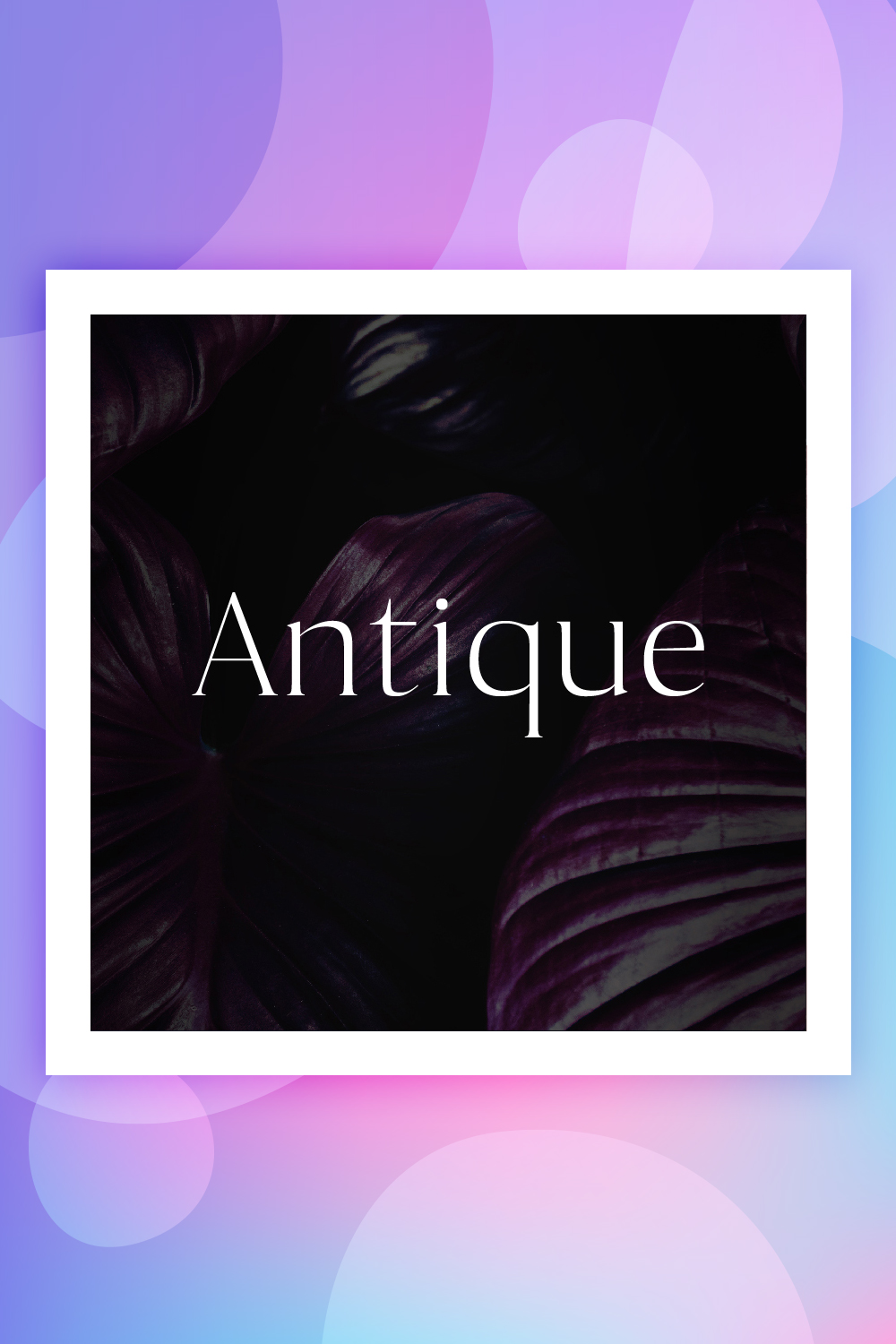
优雅清晰的排版爱好者会喜欢这种衬线字体。 古董看起来很经典,但并不普通。 这种字体略微弯曲,令人赏心悦目。 它看起来很适合多种需求。 您可以将其用于标题、横幅、基于文本的图像等。
Monalisa – Beauty Script 手写字体
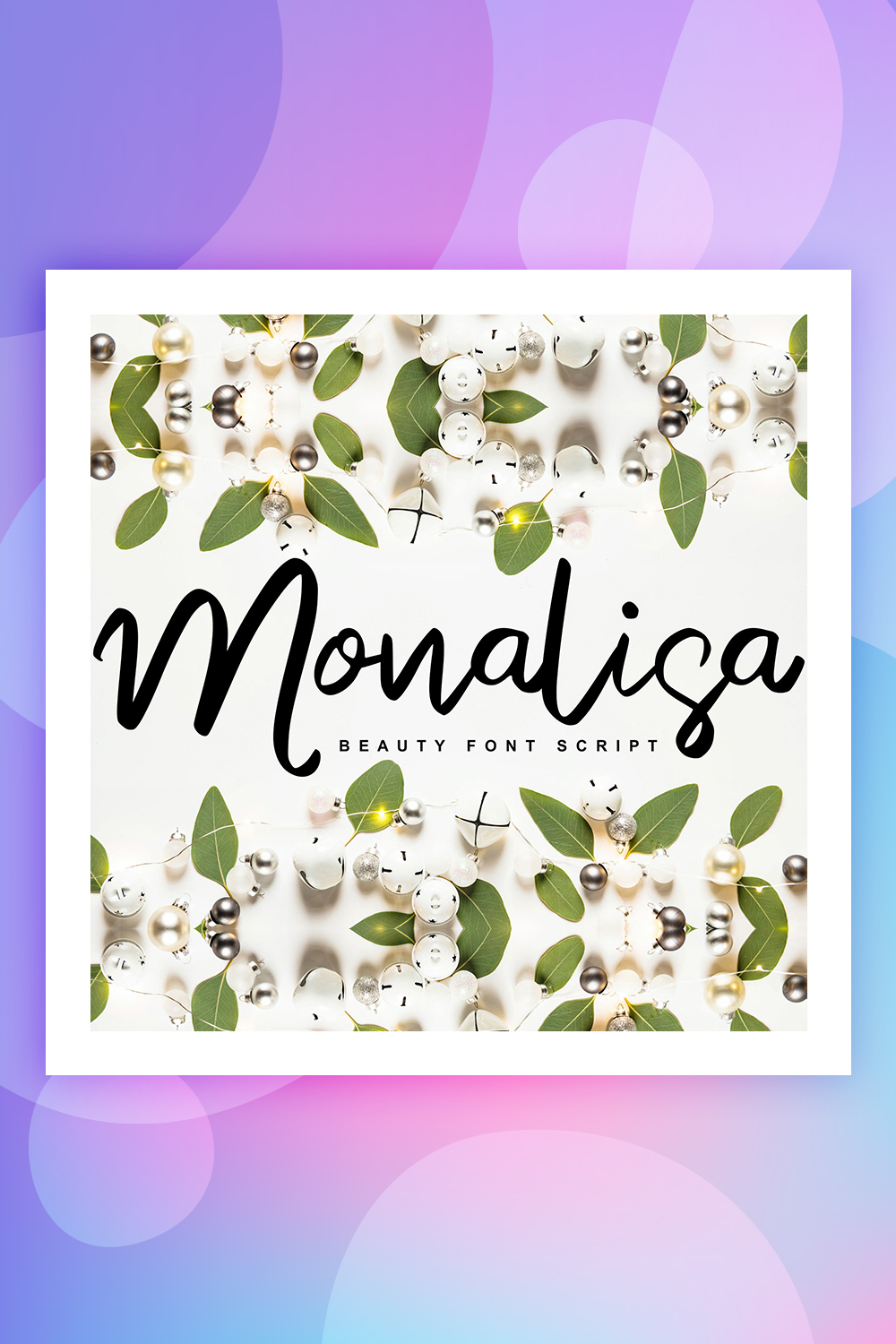
这种手写字体肯定会激发许多网页设计师的灵感。 蒙娜丽莎具有书法风格。 它可以为贺卡、邀请函、名片和品牌帖子提供真正的装饰。 通过使用这种字体,您可以使您的数字项目(例如,女性博客)在网络上大放异彩。
Qutapy – 现代脚本排版
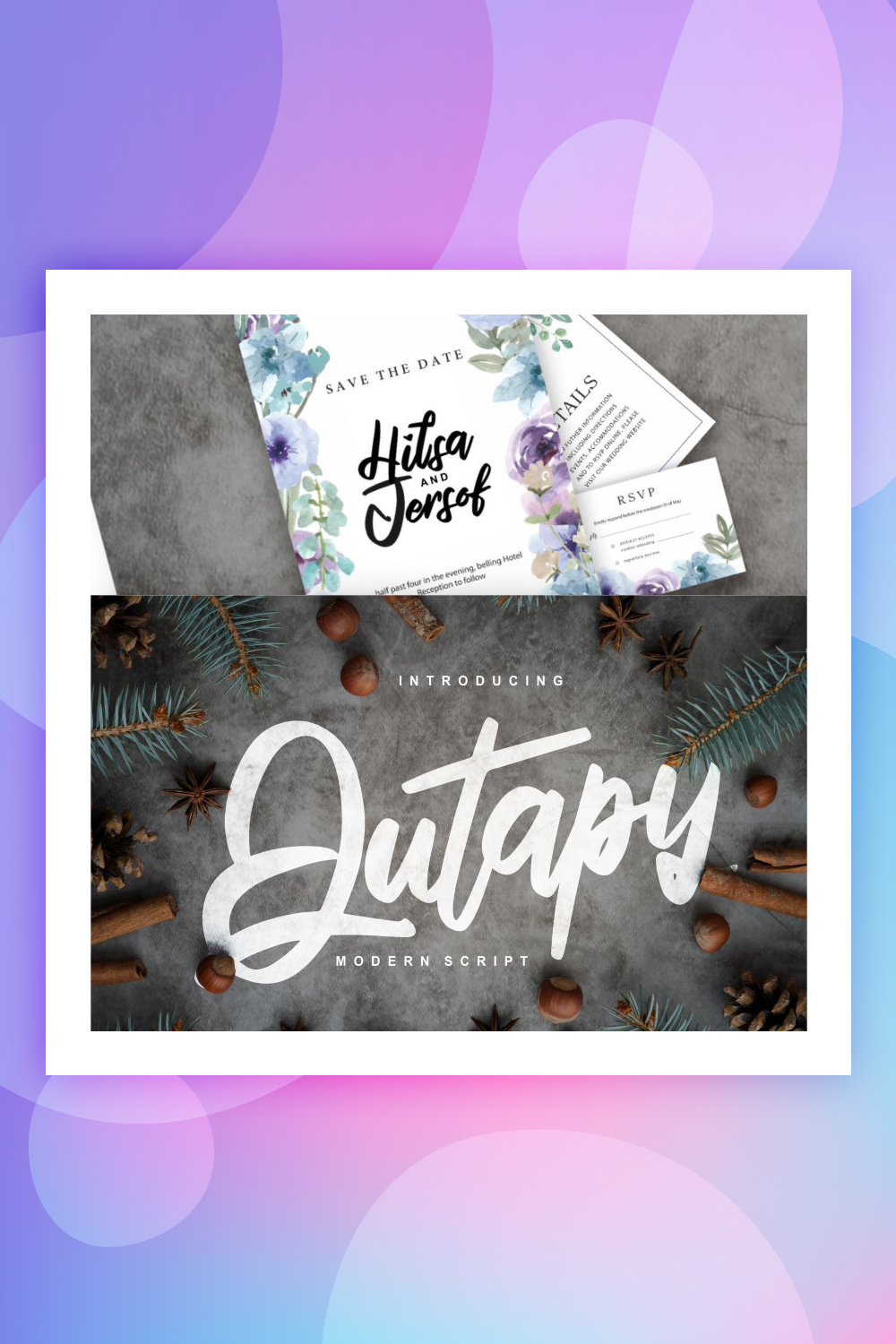
这个现代脚本为网页设计师提供了一个很好的机会来修饰他们的项目。 它适合多种需求——从邀请卡到创意业务。 字体采用正式的手绘风格。 该字体以 Open Type 格式提供。 也就是说,您可以使用一种常用程序来处理字体,例如:
Silently - 手写脚本字体
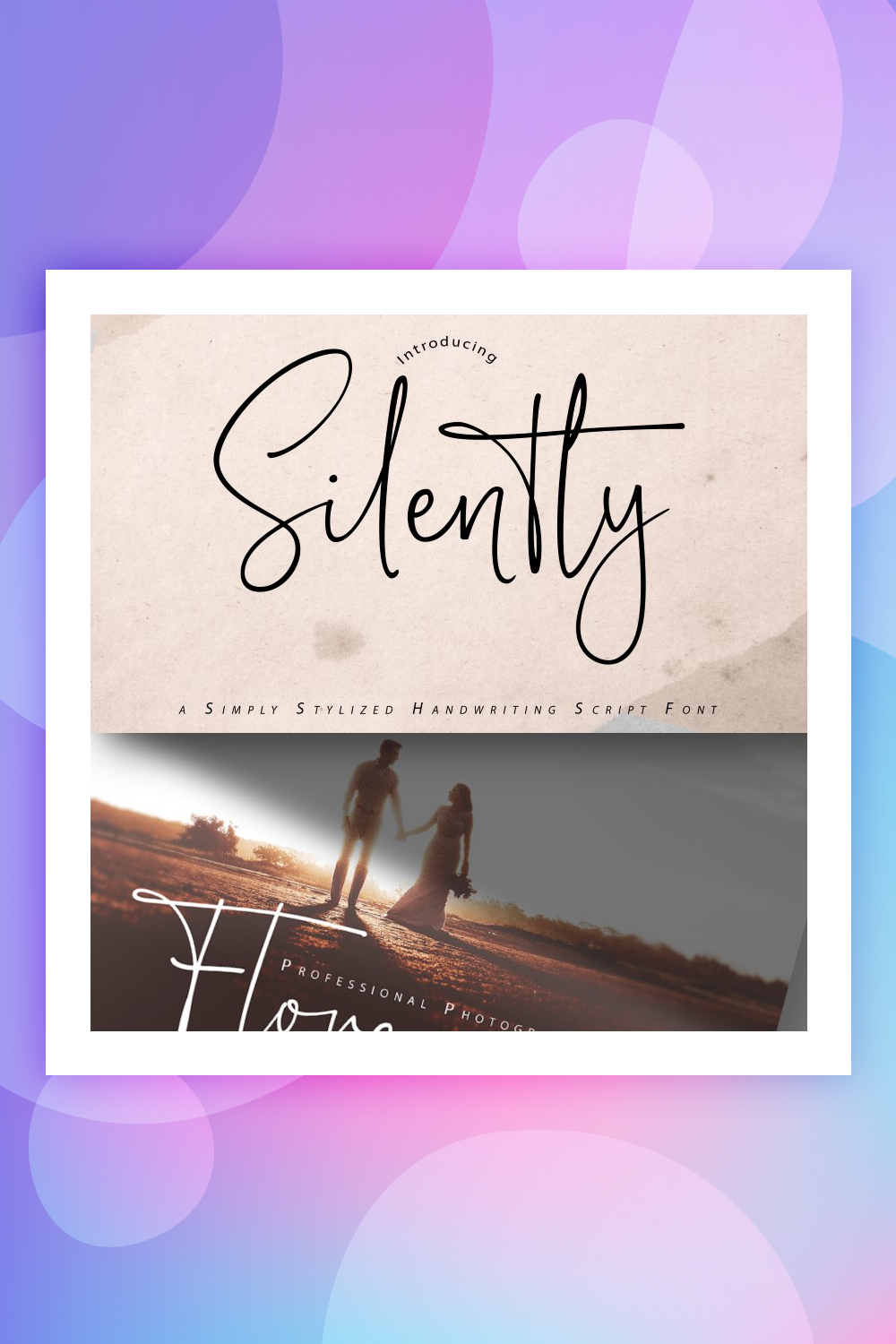
Silently 是另一种专为所有场合设计的手写字体。 它的使用范围是无限的。 由于其迷人的形状和书法风格,这种字体非常适合邀请卡和女性博客。 尽管所有字符都是手写的,但读者阅读它们不会有困难。
鬼排版
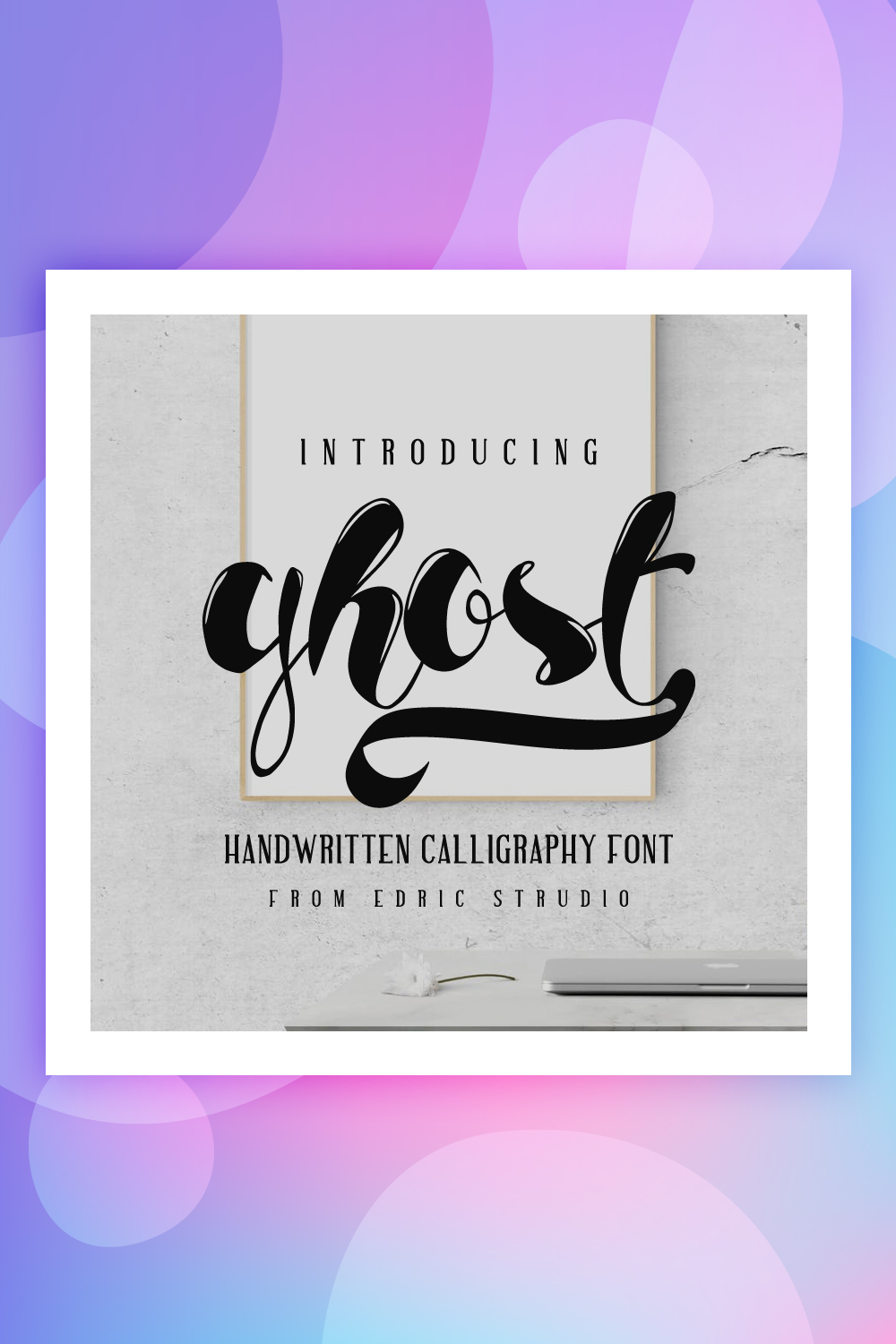
如果您一直在寻找独特、吸引人的字体,Ghost 将适合您的口味。 这种手写的网络字体大胆、醒目且引人入胜。 有很多方法可以将它整合到不同的网页设计中。 该字体将帮助您个性化任何问候、邀请、标题等。其主要特点:
- 内联和常规样式。
BadassHolliday 字体
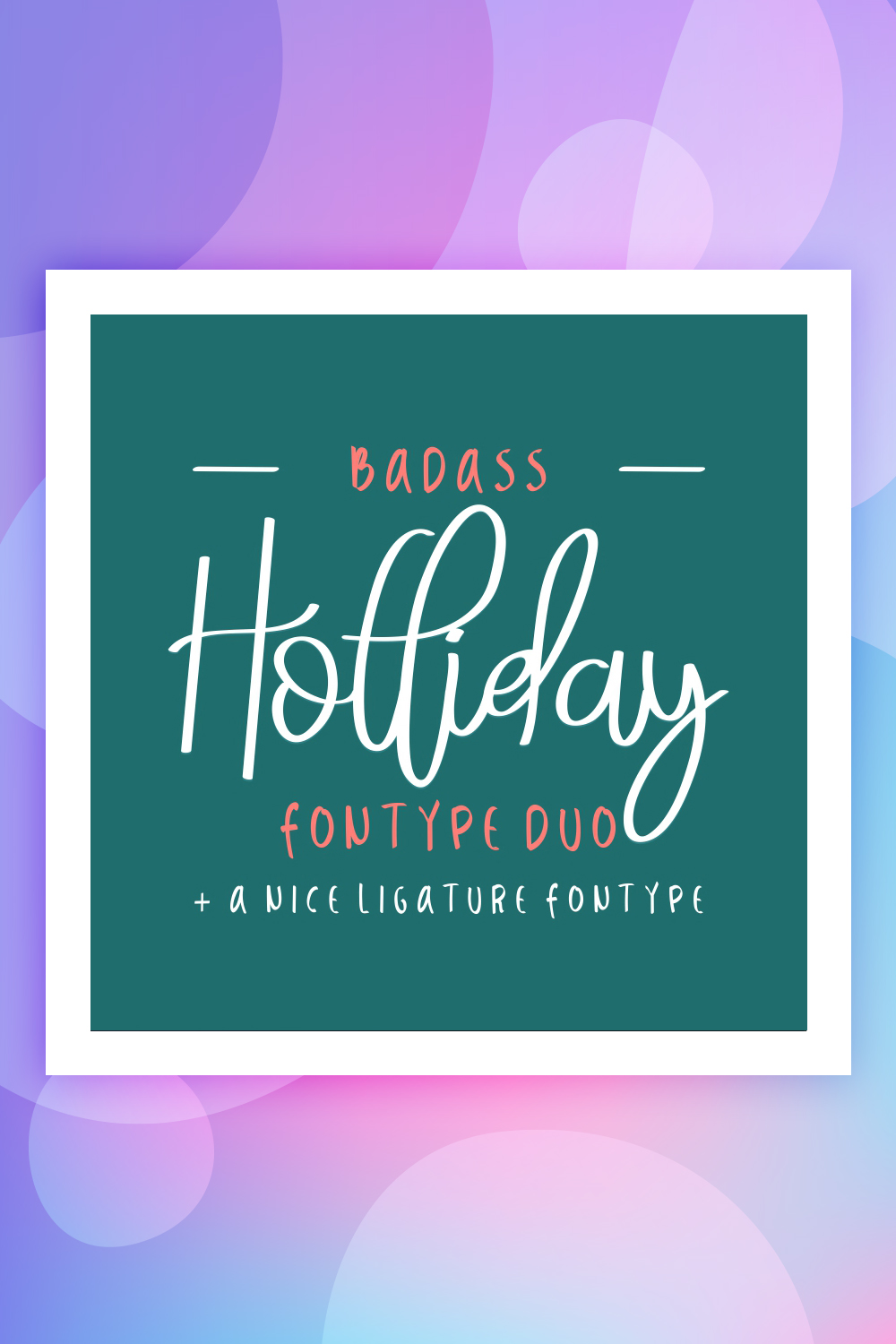
看看这款简单而引人入胜的字体,它非常适合节日贺卡、传单、问候语和许多其他需求。 BadassHoliday 可以激励许多网页设计师创造一个真正吸引人的设计。 字体是手写的,完全独一无二。 它将在 PC 和 Mac 上无缝运行。 该模板具有以下主要功能:
PancakeBatter 字体
这种华丽、可读、清晰且富有创意的字体适合多种用途。 以标志性风格制作的煎饼面糊看起来既漂亮又吸引人。 使用此字体,您可以制作精美的邀请卡并为您的企业开展有效的广告活动。 无需额外的网页设计软件,您就可以完全访问此字体。
Amber Taste 字体
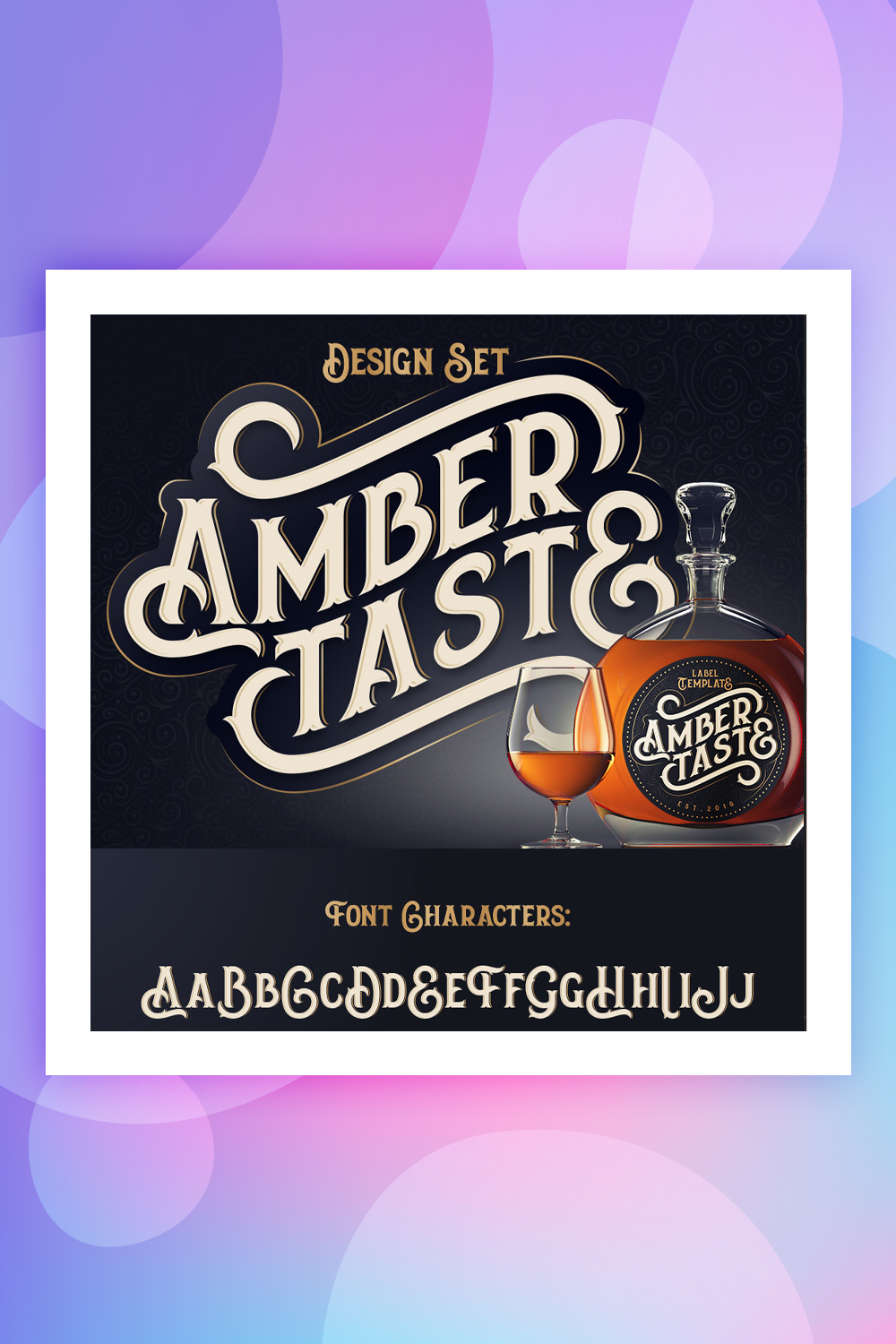
内框字体和图案字体
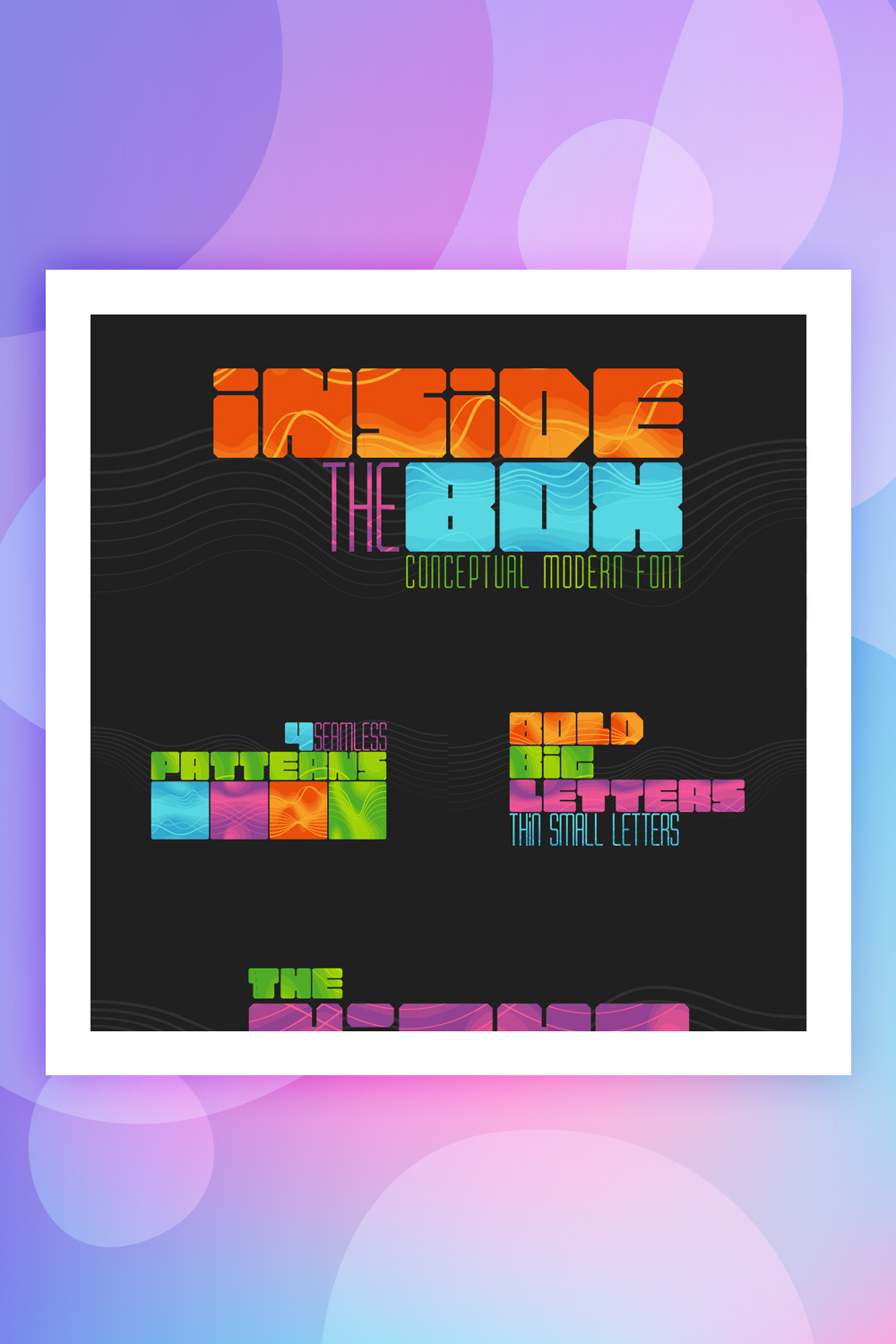
这种引人入胜的网络字体的现代外观变体将帮助您从人群中脱颖而出您的项目。 它也将作为营销目的的完美装饰。 该框包含粗细拉丁字符。 盒内有粗体大字和细小字。 该包还附带:
威士忌标签 + 设计元素字体
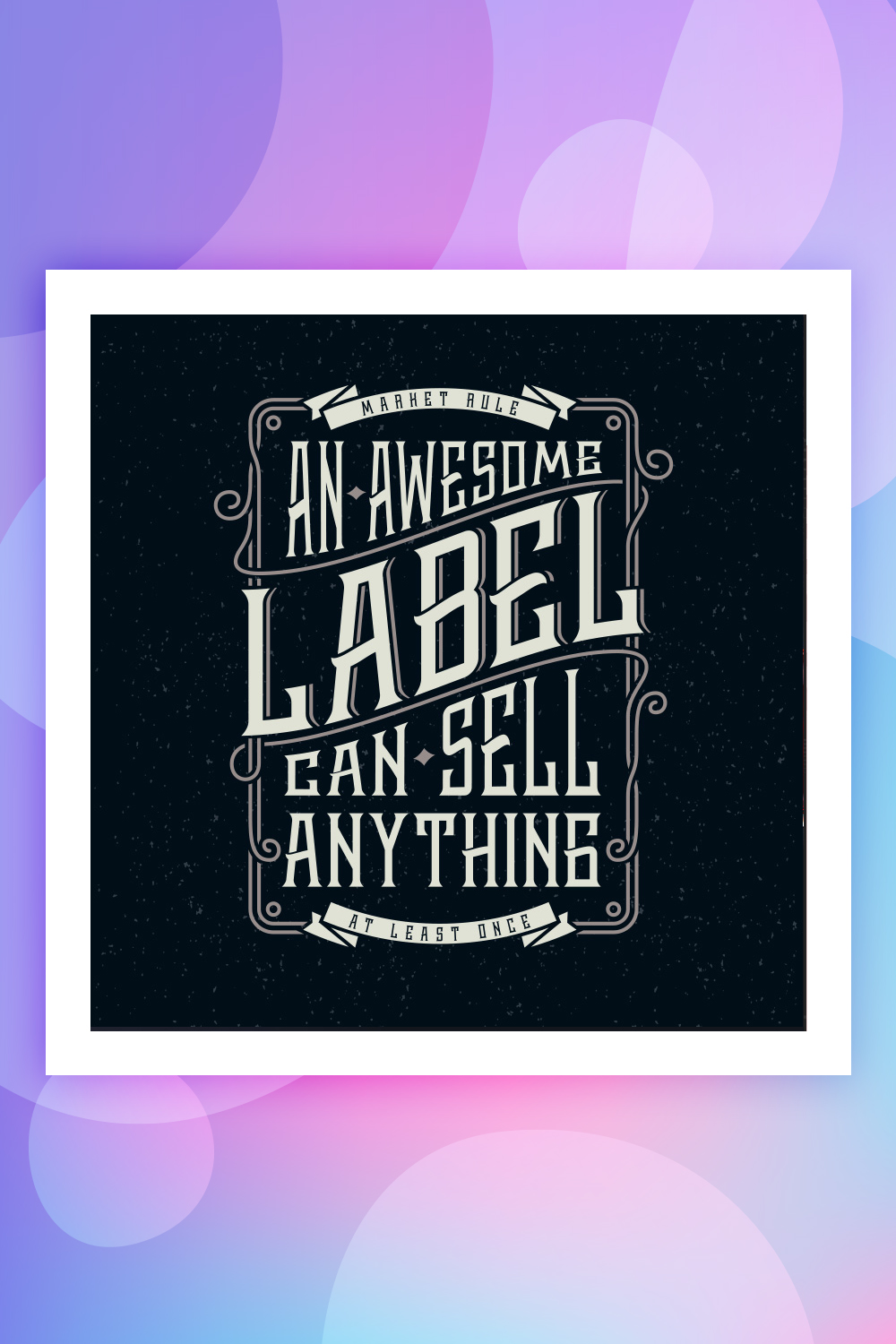
用这种创意模式出售你想要的任何东西。 它将适合任何商业和个人目的,包括推广威士忌。 该产品带有伊卡洛斯的手绘插图。 除了拉丁字母,它还包括数字和基本标点符号。
正版脚本 – 纹理类型二重奏
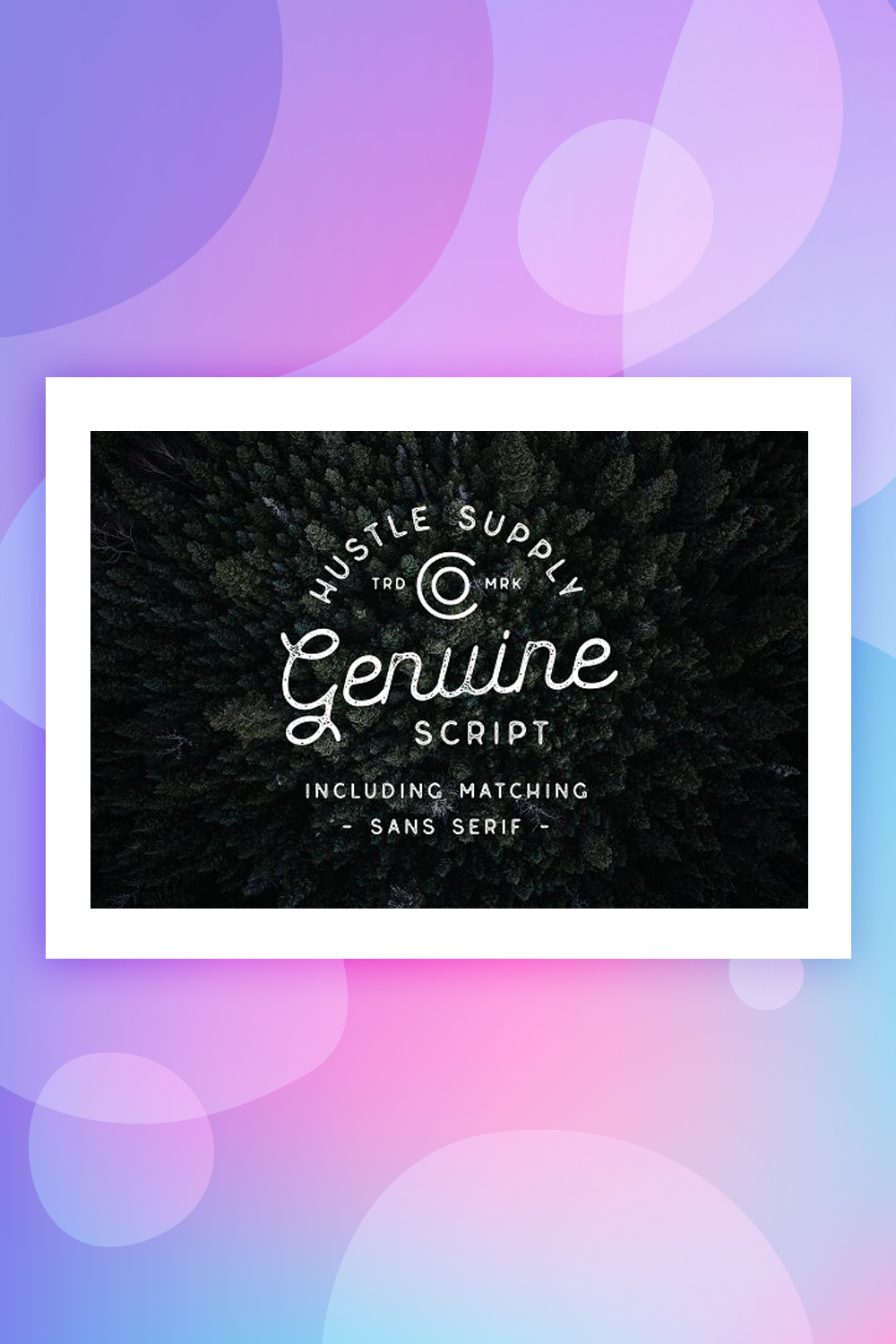
正版是由专业设计师设计的真正正品。 这是创建徽标、激励文本、基于文本的图像等的绝妙解决方案。此外,这种字体非常适合建立和提高您的品牌知名度。 它有四种字符变体,包括:
- 干净的;
- 有质感;
- 脚本;
- 扫描。
Parlor Sans 字体
如果您需要极大地强调您的美容院或理发店,Parlor 将为您派上用场。 该字体非常适合不同的营销需求。 此外,这些创意、清晰且引人注目的字母可以作为有效的商店标志。 该字体采用 OTF 格式,包括:
- 一整包拉丁字母;
- 数字;
- 标点;
- 额外的字形。
威士忌字体集